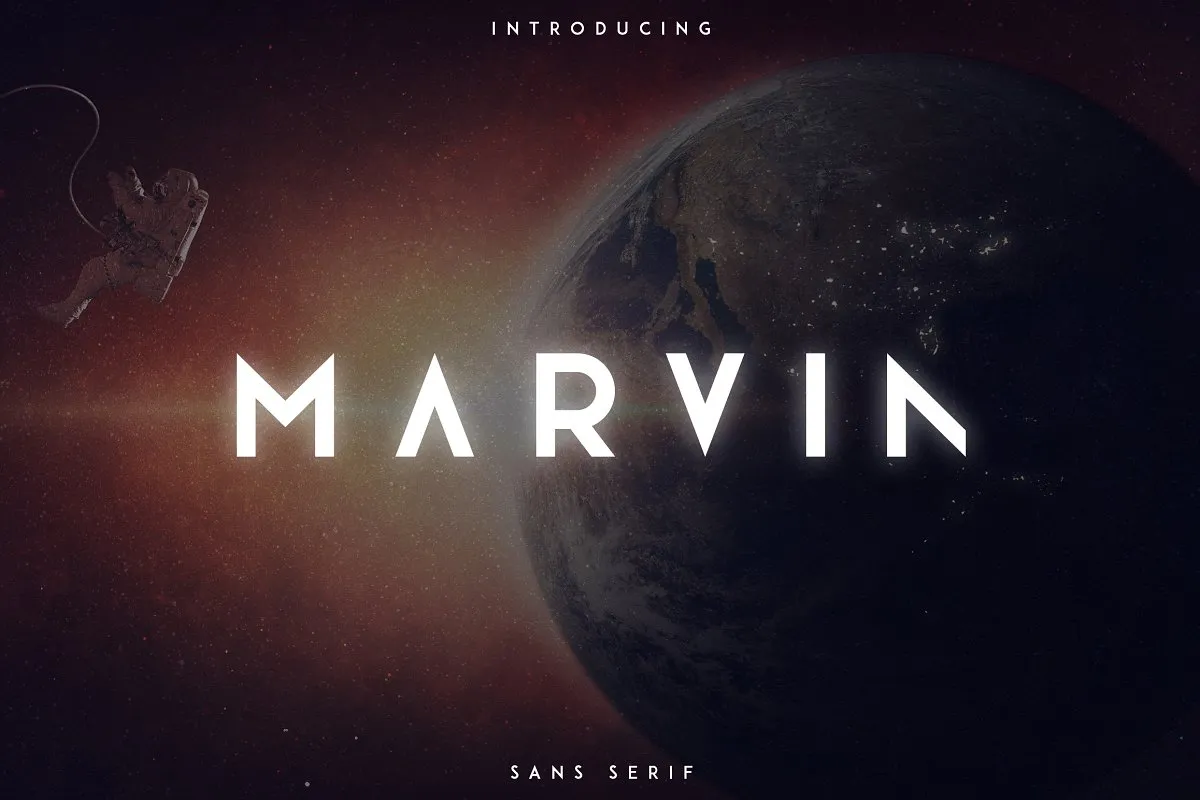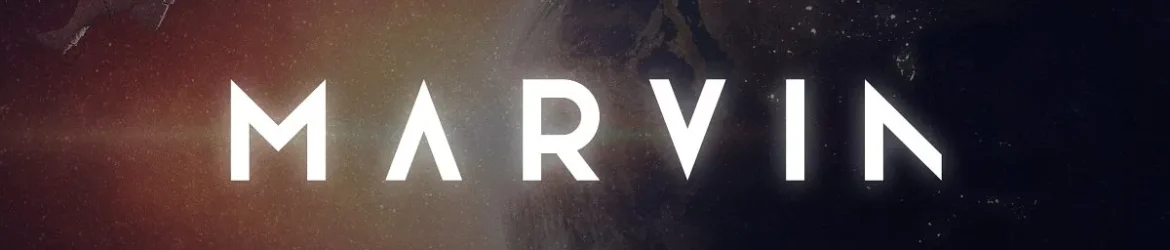
Marvin Sans Serif Typeface – Download Grátis
Esse é um novo tipo de fãntasia sans-serif que traz a essência moderna do mundo digital para seu trabalho de design. Introduzindo Marvin Typeface, uma criação da M.0Type. Com 3 tipos e suporte multilíngue, Marvin Sans Serif é um tipo robusto e limpo sem serifas. Perfeito para projetos de marca, design de móveis, embalagens de produtos ou até mesmo como um overlay de texto elegante sobre qualquer imagem de fundo. Esse fonte oferece versatilidade e eficiência em diferentes tamanhos de letra. É uma opção atraente que se destaca em qualquer projeto visual, tornando-a uma escolha ótima para designers do Brasil buscando um tipo moderno e elegante.